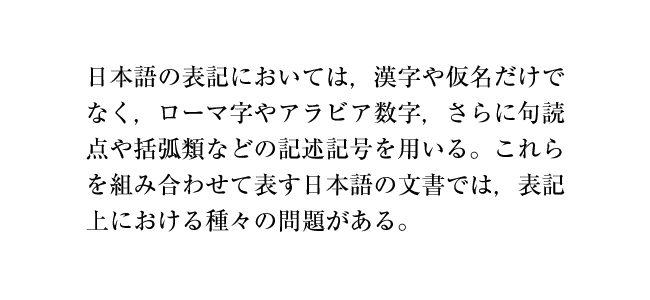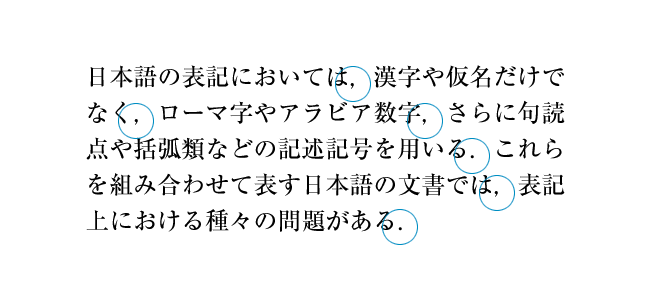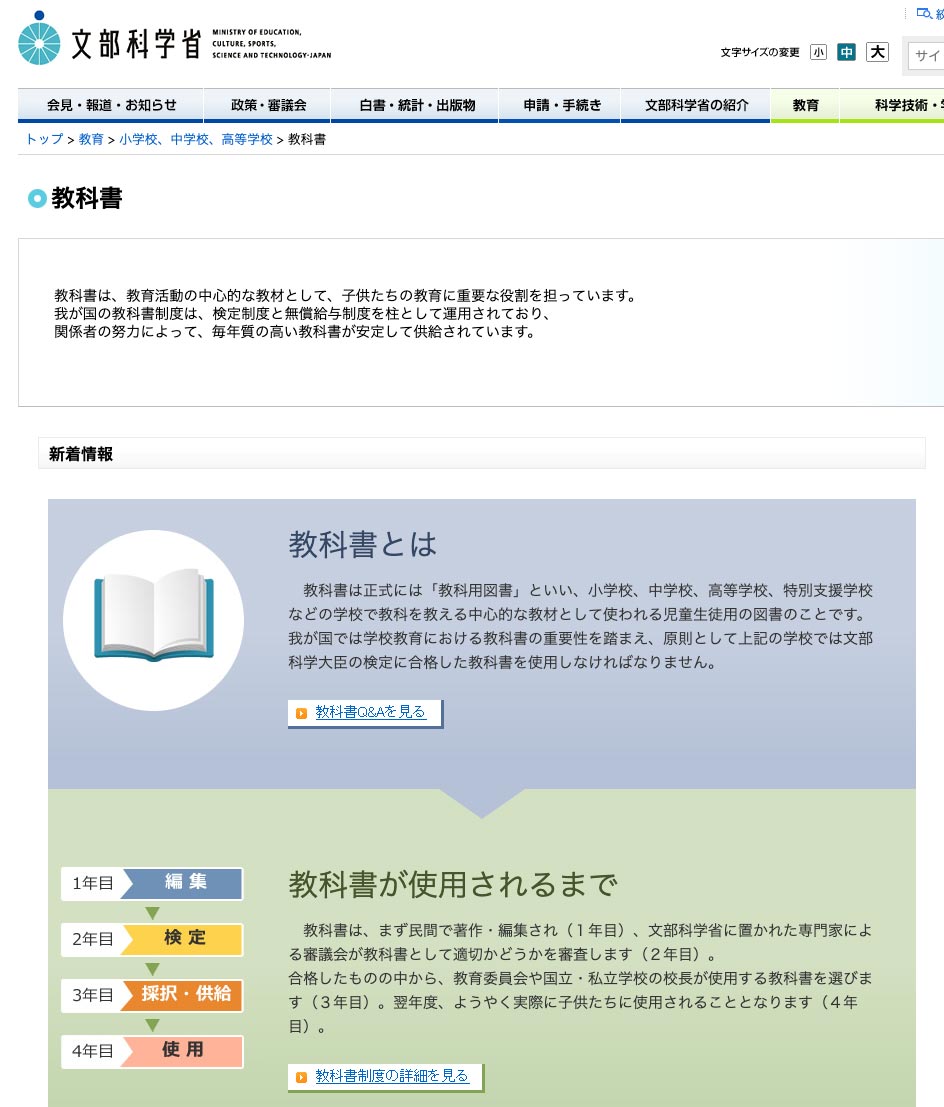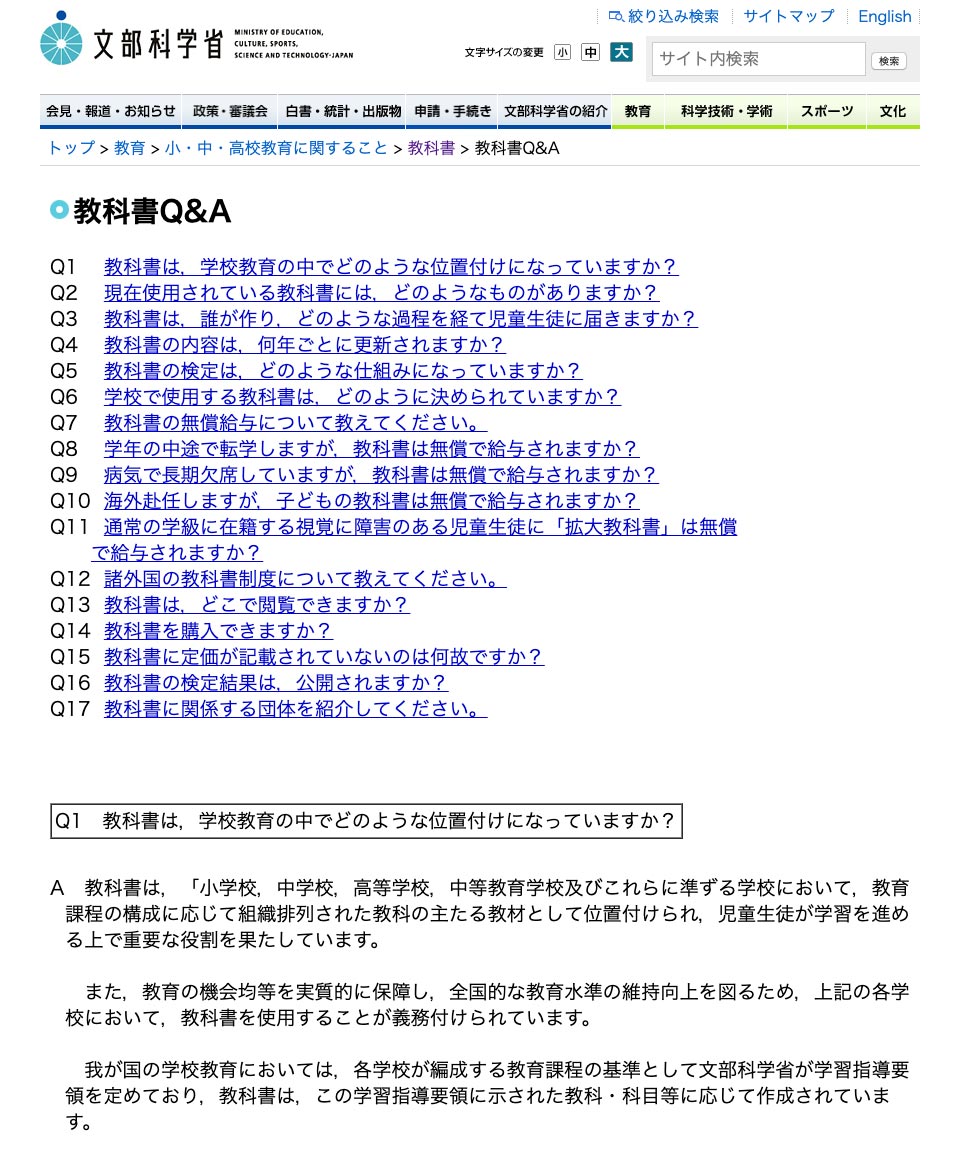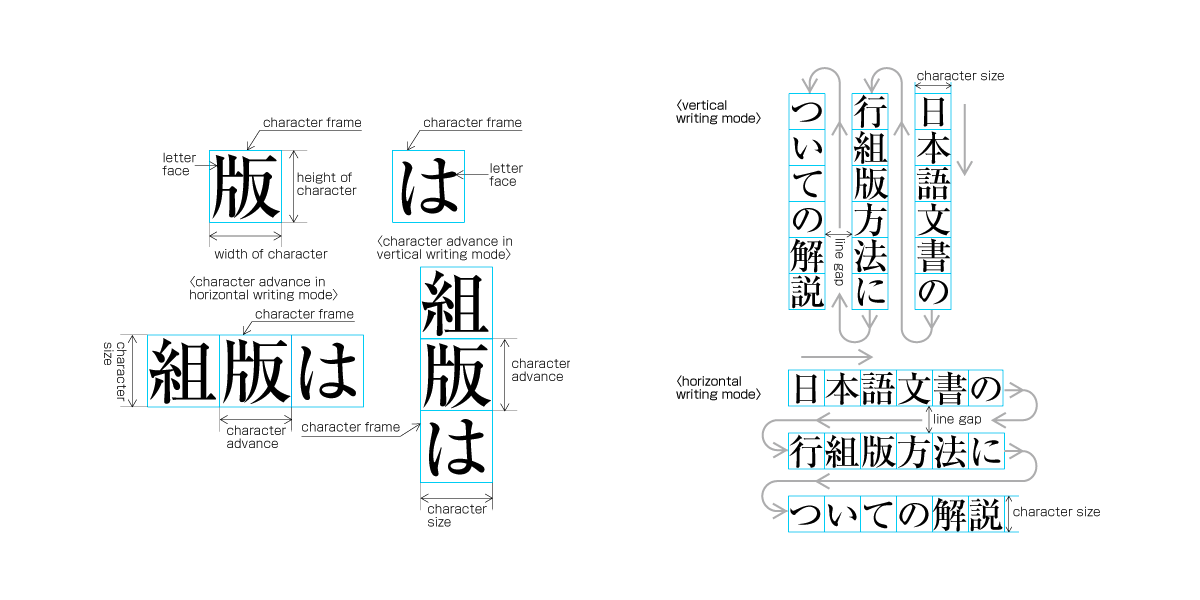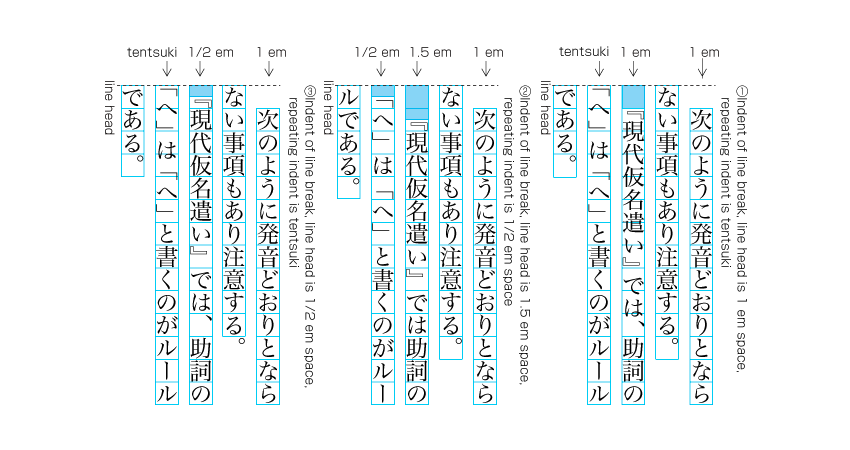
JIS X 4051 – Norm für den japanischen Werksatz
JIS X 4051 ist eine Norm des Japanischen Industriestandards (JIS) und definiert die Satzregeln für japanische Dokumente – und die hat es in sich.
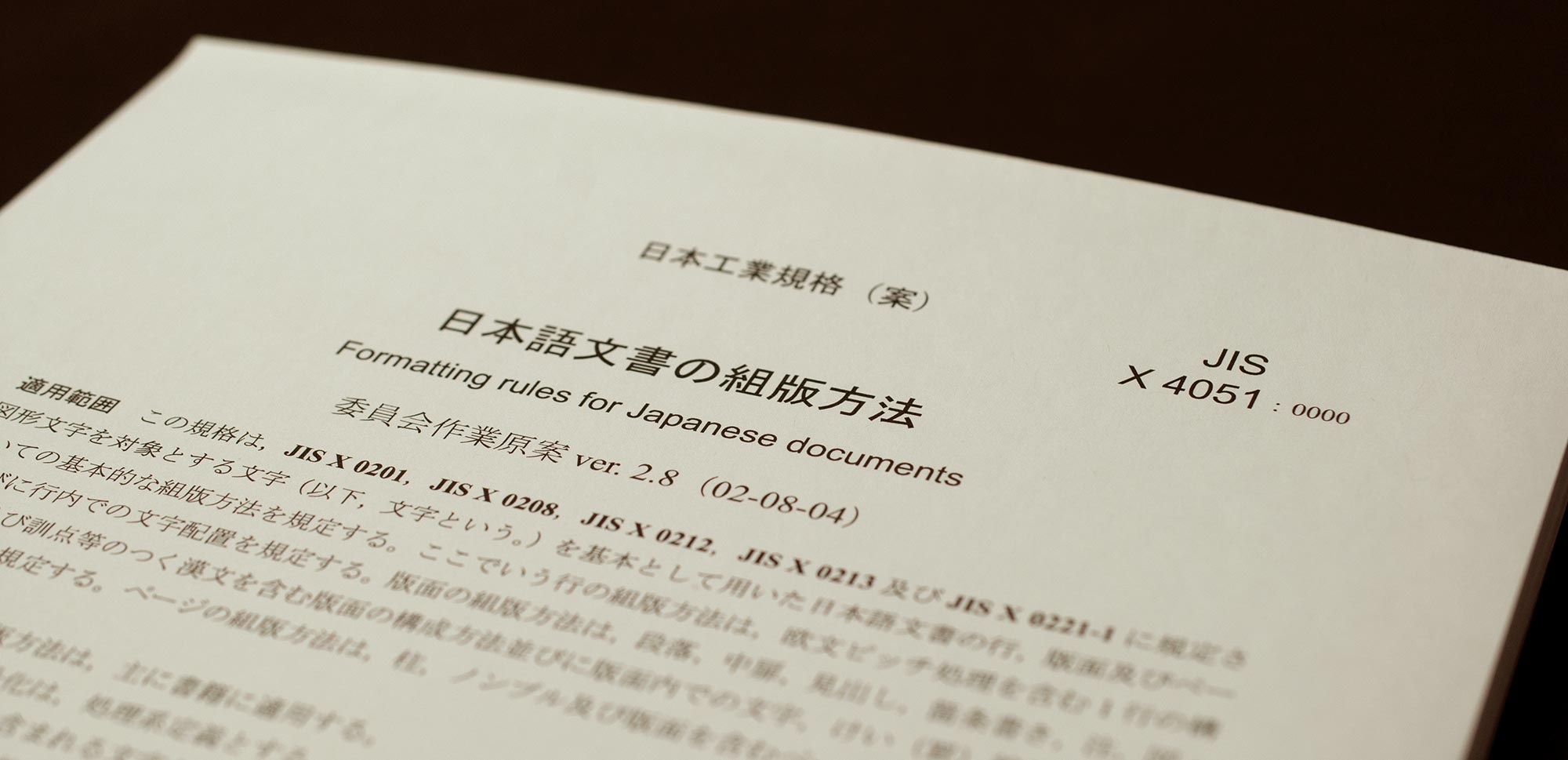
Das Regelwerk
Ein umfassendes, aber weitaus unbekanntes Regelwerk
In dem ca. 150-seitigen Schriftstück haben die Experten versucht, den allgemeinen Umgang mit Schriftzeichen, Satzzeichen, Zeilen, Absätzen, Ruby-Annotationen (was ist das?), Tabellen, Grafiken usw. beim horizontalen und vertikalem Werksatz festzulegen. Anders als die deutsche Typografie-Fibel »Detailtypografie« ist dieses komplexe Dokument kein Buch zum Vergnügen, sondern ein trockenes Regelwerk für ein bestimmtes, sehr kleines Fachpublikum. Man muss sich entweder sehr stark für dessen Inhalt interessieren oder von Beruf wegen gezwungen sein, um das Ganze durchzulesen.
Es ist schon erstaunlich, dass so ein umfassendes Dokument über den Werksatz überhaupt zusammengestellt wurde, aber es hätte vielleicht ein größeres Publikum erreicht, wenn es auch vom Akzidenzsatz gehandelt hätte. Jedenfalls soll japanische Software von Adobe (wie Illustrator und InDesign) JIS X 4051 konform erstellt worden sein, wodurch die Umsetzung der japanischen Satzmethoden aus den Bleisatz- und Fotosatz-Zeitaltern heute noch in der digitalisierten Form möglich ist. Solche Standards sind für die Softwareentwickler sicherlich hilfreich aber für normale Grafiker wie mich nichts Neues.
Dann kam man irgendwann auf die Idee, diese Standards in ein W3C-Dokument zu übertragen.
Aufklärung für Nichtjapaner
Das World Wide Web Consortium (W3C) veröffentlicht ein auf dieser Norm basierendes englischsprachiges Dokument (W3C Note) »Requirements for Japanese Text Layout«, das die Anforderungen für den japanischen Werksatz detailliert beschreibt. Dabei geht es nicht darum, wie der japanische Text mit CSS zu formatieren ist, sondern das Dokument soll hauptsächlich dazu dienen, die Nichtjapaner über die Geheimnisse des japanischen Schriftsatzes aufzuklären.
Die Zielgruppe sind Nichtjapaner, die kein Japanisch können, und auch Laien auf diesem Gebiet sollen damit besser verstehen können, nach welchen Regeln und Prinzipien der japanische Werksatz durchgeführt wird. Deshalb enthält das Dokument viel mehr Abbildungen und Hintergrundinformationen als die japanischen Vorlagen. Und obwohl auch diese Veröffentlichung nicht das ganze Spektrum der japanischen Typografie umfasst, und trotz schlechter Web-Usability, scheint sie im Gegensatz zur JIS-Norm eine relativ große Beliebtheit im Ausland zu genießen.
Und interessanterweise hat die Arbeitsgruppe des W3C diese »Working Group Note« später ins Japanische übersetzt und veröffentlicht – für Japaner, ganz nett – und das hat es in sich.
Ein Relikt aus der Vergangenheit
Dem aufmerksamen Leser wird beim Stöbern in dem Dokument gleich auffallen, dass das Komma und der Punkt in den horizontal gesetzten japanischen Beispieltexten »europäisch« sind, es sind also die Satzzeichen, die Sie kennen. In der japanischen Fassung dieses Dokuments, das übrigens auch als gedrucktes Buch erhältlich ist, betrifft das sogar die gesamten Texte. Ist das üblich? – NEIN.
Meines Erachtens ist diese Praxis ein Relikt aus der Zeit der Amerikanisierung Japans nach dem Zweiten Weltkrieg, und der Ursprung dieses Problems liegt in der Verwestlichung Japans im 19. Jahrhundert, wo das typografische Chaos begann.
Im Jahr 1952 wurden die »offiziellen Mitteilungen« vom damaligen Kultusministerium zum Thema Rechtschreibung für amtliche Dokumente bekanntgegeben. Unter anderem soll horizontal geschrieben und dabei das »westliche« Komma verwendet werden (der Punkt soll japanisch [。] sein).
Seitdem sind 70 Jahre vergangen. Von den unzähligen Behörden in Japan praktizieren heute nur noch eine Handvoll Verwaltungsorgane diese seltsame Zeichensetzung (nach eigenen Recherchen sind es Justizministerium, Oberster Gerichtshof, Wettbewerbskommission, Kaiserliches Hofamt und ein Teil des Kultus- und Wissenschaftsministeriums). Der große Rest hat sich bewusst dagegen entschieden und verwendet das japanische Komma [、] auch bei horizontaler Schreibrichtung (japanische Webtexte sind in aller Regel horizontal gesetzt, deshalb ist die Entscheidung der einzelnen Behörde bezüglich dieser Frage auf der jeweiligen Website erkennbar).
Aber eben das Kultus- und Wissenschaftsministerium ist zuständig für JIS X-Normen (X = Informationsverarbeitung). Deshalb sind wahrscheinlich auch der Arbeitsgruppe dieses W3C-Projekts die Hände gebunden, auch wenn der eine oder andere Mitstreiter etwas gegen den Einsatz vom westlichen Komma und Punkt im japanischen Text hätte. Anders kann ich mir diese irreführende Form der Vorstellung nicht erklären. Irreführend, weil die japanischen Massenmedien nichts von der »Konvention« der Behörden halten und konsequent das japanische Komma verwenden. Zeitungen, Zeitschriften, Fernsehen, Internet, soziale Medien … im alltäglichen Leben der Normalbürger ist das »andere« Komma fehl am Platz.
Papier ist geduldig, Schulbücher sind es auch
Schulbücher haben Vorbildfunktion. Die Satzzeichen in den Schulbüchern müssen deshalb auch vorbildlich verwendet sein. Und wer kontrolliert die Schulbücher? – na, das Kultusministerium natürlich. Die horizontal gesetzten Schulbücher in Japan (Soziologie, Mathematik, Naturwissenschaft, Musik, Englisch u.a.) sind deshalb übersät mit dem westlichen Komma, d.h., die Schüler haben ziemlich lange Zeit, um sich diese vom Staat »empfohlene« Schreibweise anzueignen. Aber das geschieht nicht, als hätten sie in der Schule nichts gelernt.
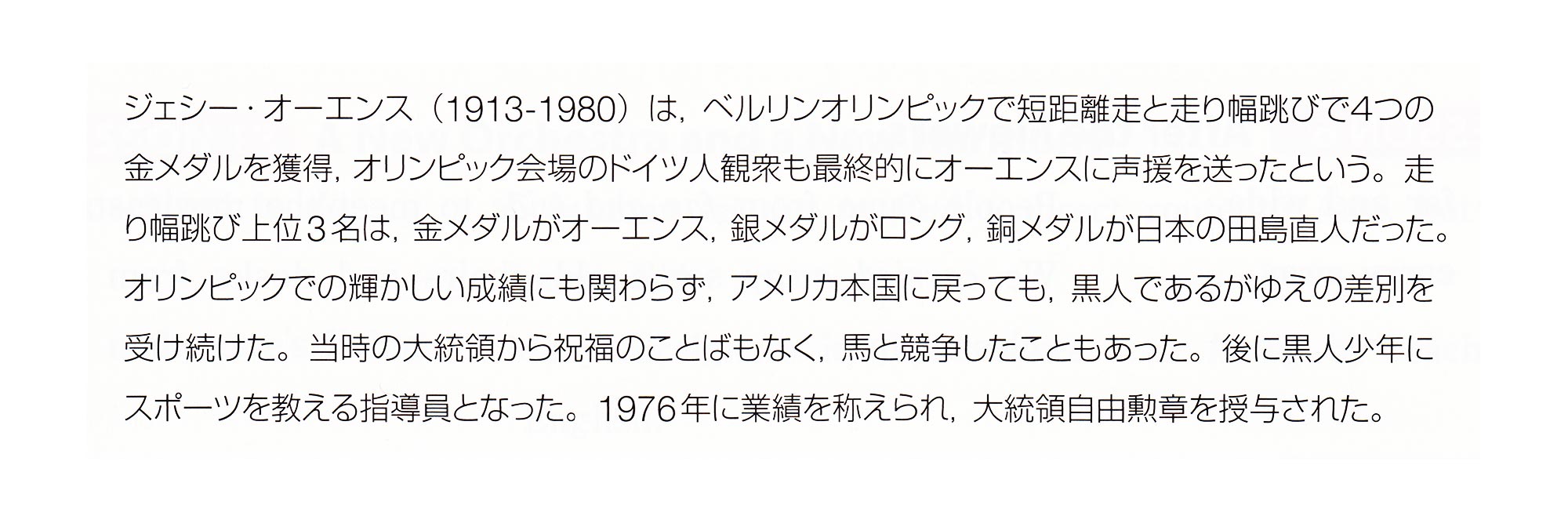
Übrigens: Einige wissenschaftliche Gesellschaften und Institute in der japanischen EDV-Branche haben eigene Hausregeln für die Schreibweise. Sie schreiben ihren Mitgliedern vor, in ihren Beiträgen für wissenschaftliche Fachzeitschriften westliche Kommas und Punkte zu verwenden. Außerdem soll es in technischen Fachbereichen (Universitäten, Forschungsinstitute u.ä.) relativ viele Menschen geben, die weder das japanische Komma noch den japanischen Punkt verwenden, da sie sich stets mit mathematischen Formeln beschäftigen und das ständige Umstellen der Tastatur nur lästig finden. Sie sind aber eindeutig Ausnahmegruppen, die dennoch nicht außer Acht gelassen werden sollten.